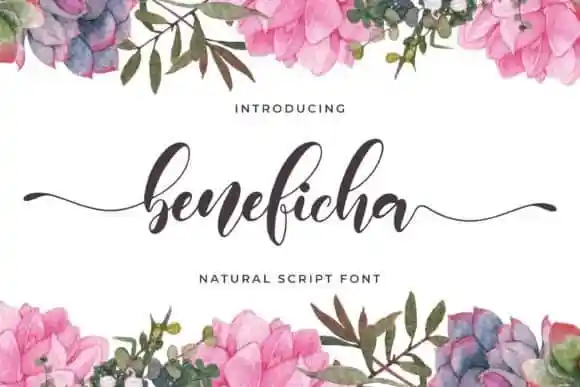
Beneficha Script Font é uma elegante escolha para quem busca uma fonte de script moderna que pode revigorizar seu design, oferecendo textos encantadores e sofisticados. Este elegante tipo de letra do século XXI ganha vida graças a suas ligações suaves e alternativas perfeitas, criando um aspecto luxuoso e contemporâneo em qualquer texto que você criar. Com seu design natural, Beneficha Script Font parece plagiado de uma pintura moderna ou escrita por um mestre do artesanato. Além disso, a fonte é PUA codificada, permitindo acesso fácil a todos os incríveis caracteres e swashes que ela tem para oferecer. Seja você um designer gráfico experiente ou iniciante, Beneficha Script Font vai definitivamente encantar seu trabalho de design.